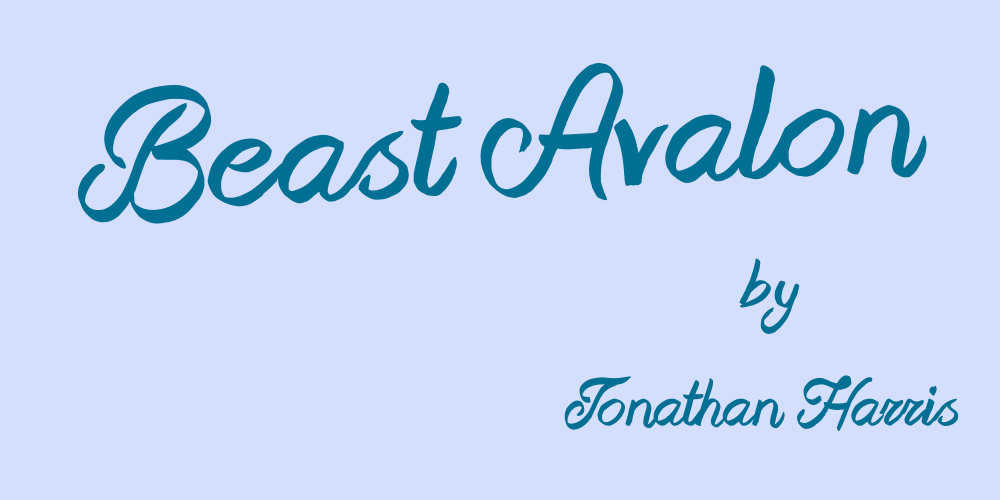
A fonte ‘Beast of Avalon’ é um script elegante e versátil, perfeita para criar designs únicos e sofisticados. Criada pelo designer Hamilton, esta fonte oferece uma gama de opções que vão desde linhas delicadas e femininas até traços mais robustos, adequando-se a diversas necessidades gráficas. Seja você um criador independente ou profissional, este script atende as suas demandas. Se estiver procurando por algo diferenciado para seus designs pessoais, esta fonte é uma ótima opção. No entanto, se desejar usar esta fonte em um projeto comercial, como a criação de materiais impressos ou desenvolvimento de software, será necessário adquirir uma licença. Para mais informações sobre como utilizar esta fantástica fonte para seus projetos comerciais, visite o site oficial http://www.tattoowoo.com ou entre em contato diretamente conosco através do email .